השאלון עם מתן גירו
הכירו את מתן גירו, בן 26, שנולד בשנת 1998 וגדל בראשון לציון, שם הוא מתגורר גם היום. מתן הוא סטודנט לתקשורת חזותית ב־HIT, עוסק בעיקר בעיצוב ואיור, ואוהב במיוחד את עולם הפרינט. האהבה שלו לעיצוב התחילה כבר בילדות, כשהיה משחק בטקסטים אקראיים, מחליף פונטים בשביל הכיף ובוחן עטיפות אלבומים כאילו היו יצירות אמנות. מאז, הסקרנות הזו מלווה אותו בכל מקום – ברחוב, במוזיקה ובתרבות שסביבו. מתן אוהב את הוורסטיליות שבעיצוב ואת העובדה שכל אחד יכול להרגיש משהו אחר מאותה עבודה. בעיניו, עיצוב טוב הוא כזה ששומר על פשטות אך מצליח לעורר מחשבה ורגש, ומהווה דרך לייצר חיבורים בין אנשים, רעיונות ותכנים, תוך כדי סיפור שמדבר גם ברמה האישית וגם בצורה רחבה ואוניברסלית. כשהוא לא עובד, אפשר למצוא אותו עם חבר שלו או עם חברים סביב אוכל או בתי קפה כיפיים, ולעיתים גם סתם בבית מול הטלוויזיה.
היי מתן, מה שלומך? איפה אנחנו תופסים אותך השבוע?
הכול טוב, תודה ששאלתם. אני כרגע בחופשה מהלימודים, וזה נותן לי זמן להתפקס על פרויקטים אישיים ולעשות דברים בשביל עצמי בעיקר.
איפה אתה עובד עכשיו?
כרגע אני מנהל חנות ב־Factory54, מה שמחבר אותי לעולם האופנה גם מהצד הפרקטי והיומיומי, ובנוסף מתמקד בפרויקטים אישיים ועצמאים שאני מפתח עם הרבה רצון לתפוס תאוצה גדולה בעולם העיצוב ולהתחיל ליצור דברים גדולים.
אתה מעדיף לעבוד לבד או בצוות?
יש קסם בעבודה לבד שאני תמיד אוהב, השקט והשליטה המלאה, אבל בצוות אני מגלה רעיונות שלא הייתי מגיע אליהם לבד. השילוב בין השניים הוא מה שהכי מפרה אותי.
על איזה פרויקט מעניין עבדת לאחרונה?
לאחרונה עבדתי על מגזין שמתעד את השהות שלי בלונדון, שהות שנמשכה שבועיים וחצי בעקבות סגירת שמיים בחודש יוני. זה היה שילוב בין סיפור אישי, צילומים ועיצוב גרפי, חוויה מאוד עוצמתית שהפכה לזיכרון שאני מחכה כבר להוציא לדפוס כמזכרת.
מעניין. מה הדבר הכי טוב שקרה לך השנה?
להרגיש יותר יציב ובשל אחרי תקופה לא פשוטה. בזכות זה אני מרגיש שאני יכול להוציא את עצמי החוצה, ולדבר את השפה היצירתית שלי בביטחון, גם במקצועי וגם באישי.
מה גורם לך להתרגש ולרצות לעצב וליצור?
מוזיקה, אופנה, טבע ואנשים ברחוב. הרבה השראה מגיעה מהרחוב עצמו ומהדברים שאני רואה בדרך, שילוב של סיטואציות קטנות, רגעים יומיומיים ותמונות חולפות שהופכות לנקודת פתיחה לעולם ויזואלי חדש.
מה אתה עושה כשאין לך מוזה?
לפעמים עוזר לי פשוט לסגור את המחשב, לשמוע שירים ולהתחיל לאייר כל מה שעולה לי בראש. בנוסף אני מוצא את עצמי הרבה פעמים נכנס לגלרייה בטלפון, גולל בין התמונות האחרונות שצילמתי ומשם קופצים רעיונות גדולים שהיו כל הזמן הזה מתחת לאף.
מה אתה עושה בשביל הכיף?
אני מאוד אוהב לעשות הליכות עם אוזניות, מאוד אוהב יוגה ומדיטציות וגם סתם לשבת עם חבר שלי בבתי קפה.
יש לך הרגל מגונה?
בעיקר לעבוד על פרויקטים עד השעות הקטנות של הלילה.
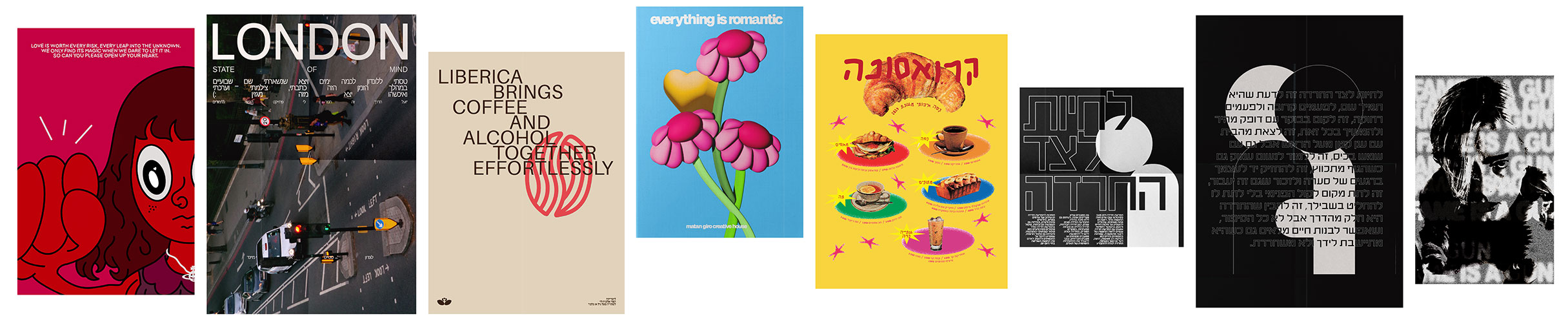
אוסף כרזות שהכין מתן במהלך השנה האחרונה. הכרזות נעות בין עולמות של מוזיקה ותרבות, מחקרי מיתוג חזותי, וגם נוגעות בחוויה האישית שלו בהתמודדות עם חרדה על גווניה השונים. כל כרזה עבורו היא ניסוי ויזואלי שונה – לעיתים חיבור אסתטי, לעיתים פרשנות על תנועות תרבות רחוב, ובפעמים אחרות ניסיון לתת צורה לרגשות מורכבים. מתן מספר כי "העבודות האלו יושבות על התפר שבין אישי לציבורי, בין ניסוי עיצובי לבין סיפור אישי, והן מבחינתי תחנה חשובה בהתפתחות שלי כמעצב וכיוצר.״
יצא לך לטייל בחו״ל?
כן, טיילתי הרבה בארה״ב ובעיקר באירופה, תמיד חו״ל ירגיש לי מקור השראה מטורף (גם הארץ), אבל כיף לראות תרבויות שונות ואנשים שונים מהיום יום הרגיל.
מה משך אותך לתחום?
עוד בתור ילד בן 7 הייתי נכנס ל־Word, כותב משפטים רנדומליים ומשחק עם הפונטים המובנים שם. אהבתי לגלות איך כל פונט גורם לי להרגיש משהו שונה. כבר אז הבנתי שמה שמסקרן אותי בעיצוב הוא הצד הרגשי, איך ויזואליות מצליחה לעורר תחושה עוד לפני שמבינים את התוכן. בנוסף, מאז ומתמיד עטיפות של אלבומים משכו אותי, הייתי ממש שופט אלבומים לפי העטיפה שלהם, וזה גרם לי להבין עד כמה עיצוב משפיע על הדרך שבה אנחנו תופסים חוויות תרבותיות.
איזה מרצה השפיע/ה עליך במיוחד?
בקורס יסודות העיצוב לימדה אותי שקד גול פרסיה. התשוקה שלה לשיח סביב העבודות של כולם והיכולת לפרק כל פרט קטן היו דברים שהתחברתי אליהם מאוד והשפיעו על הדרך שבה אני מתבונן ביצירה.
איזה מעצב/ת השפיע/ה עליך יותר מכל?
וירג'יל אבלו הראה לי איך רעיונות יכולים לעבור בחופשיות בין אופנה, אמנות, מוזיקה, תרבות ורחוב, לאחד את הכל ביחד וליצור שפה חדשה בלי גבולות.
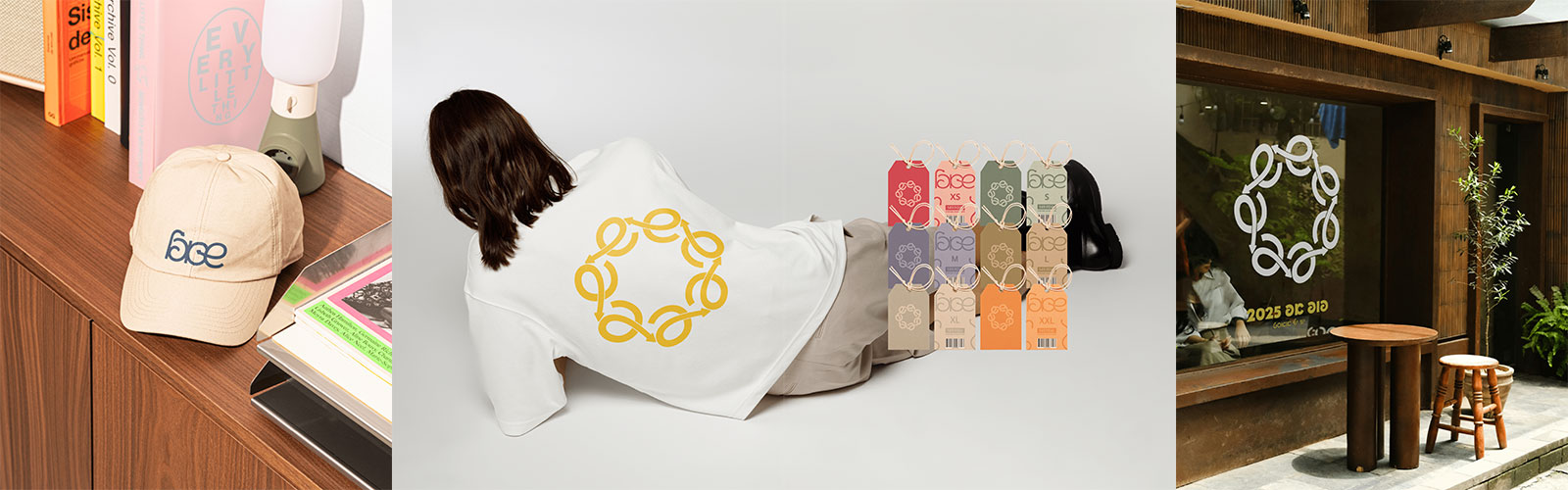
פרויקט מיתוג שיצר מתן יחד עם קורל פלינט, חברה טובה ללימודים. השניים יצרו מותג בגדים – "הרצון היה לשבור גבולות של מגדר וליצור מרחב פתוח לכולם". הקו העיצובי מתבסס על צבעים שקטים ונקיים, המדגישים את הפשטות והנוחות של הבגד עצמו. הבחירה בבדים איכותיים משקפת גישה מודעת וצלולה, שמאפשרת חופש אמיתי בבחירה האישית.
במה היית עוסק אם לא היית מעצב?
קשה לי לחשוב על משהו אחר, כי מאז שאני זוכר את עצמי אמנות היא כל חיי – באופנה, בדיגיטל או באיור. אבל הכי רחוק שאני מצליח לחשוב זה להתעסק בפיסול וקרמיקה, בגלל שאמא שלי התעסקה בזה המון שנים זה משך אותי גם.
איפה אתה רואה את עצמך בעוד חמש שנים מהיום?
מוביל סטודיו עצמאי שמחבר בין מיתוג, אנשים ואמנות, יוצר שיתופי פעולה בינלאומיים, וממשיך לפתח שפה אישית שמבוססת על חיבור בין עולמות שונים.
רוצה להמליץ על ספר עיצוב?
כן, הספר הראשון שקניתי בתחום The Graphic Design Bible. אמנם הכי קלאסי אבל גם מה ששינה אצלי הכל, הוא היה עבורי שער לעולם הזה, והראה לי כמה עיצוב יכול להיות גם כלי עבודה וגם מקור השראה.
אתר השראה מדליק שאנחנו לא מכירים?
same.energy – אתר שיש בו הכול מהכול, ותמיד מצליח לגרום לי להתאפס על משהו ספציפי לאותו הרגע.
באיזה פונט אתה רוצה שיכתבו על המצבה שלך?
פלוני־יד. חד משמעית.
יש לך המלצה מוזיקלית?
בעיקרון בזמן האחרון אני שומע בלי סוף את האלבומים החדשים של אדיסון ריי, לורד וטיילר דה קריאטור. באופן כללי ההשפעה הכי גדולה שלי ביקום זאת המלכה האם לנה דל־ריי.
מהי משמעות החיים?
למצוא רגעים קטנים של חיבור לעצמך, לאנשים סביבך ולעולם שאתה יוצר בתוכו. ומוזיקה טובה כמובן!
איך עולם העיצוב ייראה בעוד עשור?
אני חושב שהוא יהיה הרבה יותר משולב עם טכנולוגיה ובינה מלאכותית, אבל עדיין ישאר הצורך במגע האנושי ברגש ובאותנטיות שרק מעצבים מביאים.
מה שם החיבה שלך?
חברים קוראים לי מתני, והיום אחרי שפתחתי את האתר שלי – גם mgch תופס 🙂
קיצור מקלדת אהוב.
Cmd+Z – שתמיד מציל אותי בשעת צרה.
כתוב בבקשה את המילה הבאה בכתב היד שלך: